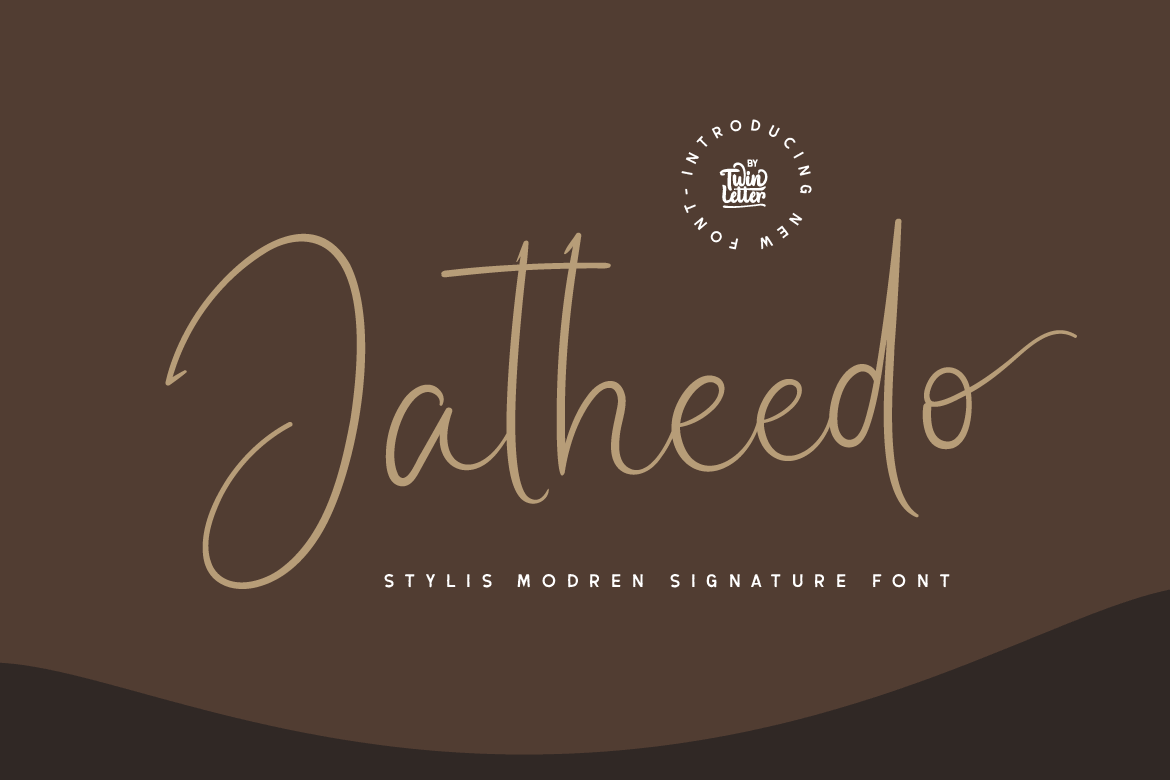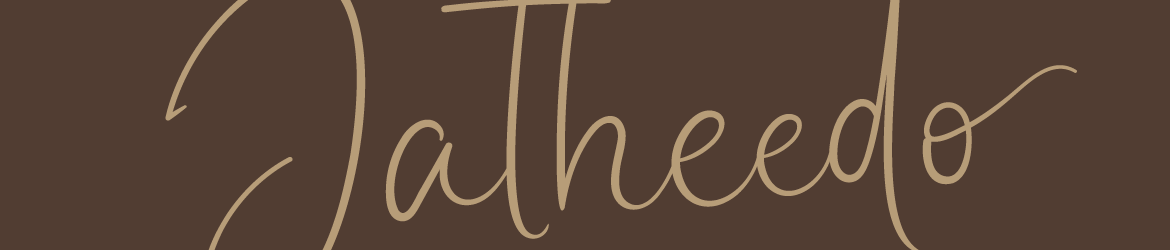
A Jatheedo Font é uma tipografia criada a partir de traços originais feitos à mão que tem a capacidade única de anestesiá-lo com sua beleza e sofisticação, tornando-a perfeitamente adaptável para qualquer projeto visual. Com um forte carácter próprio, essa fonte se destaca tanto quando usada sozinha quanto quando combinada com letras de sans ou sans serif, proporcionando uma arquitetura gráfica única ao seu trabalho. Seja você um designer de ponta ou um iniciante que busca dar vida à sua arte visual, Jatheedo é a escolha certa para iluminar seus trabalhos com estilo e originalidade. Descubra como essa fonte poderia transformar o aspecto de seu próximo projeto.